Sumergirse en el mundo de la tipografía es emprender un viaje al pasado. En este curso aprenderás a estudiar las raíces de una fuente para reinterpretarla en digital, una forma de homenaje al pasado de la mano de Oscar Guerrero —Diseñador gráfico y especialista en diseño de tipografía— quien te guiará paso a paso con el método de revival tipográfico.
Si quieres darle una nueva vida digital a una tipografía clásica, aprende junto a Oscar y sumérgete en caracteres, formas y manchas.
Conocerás el trabajo de Oscar Guerrero, su experiencia como diseñador de tipografía y cómo se introdujo en el mundo del diseño de letras. Descubrirás su pasión por el diseño a través de sus principales influencias y proyectos de rescate de tipografías.
Verás qué es el revival tipográfico —la arqueología de las tipografías— por medio de una serie de proyectos relevantes.
Como punto de partida para tu proyecto, buscarás muestras de fuentes clásicas en libros, señales urbanas o similares. Una vez hayas elegido una tipo, la analizarás para determinar sus características principales y ver los aspectos estructurales y rasgos únicos de la misma.
Oscar te explicará todos los parámetros de diseño básico para comprender la forma tipográfica. Aprenderás sobre aspectos que pueden cambiar radicalmente una letra, como métrica y proporción, estructura, color y contraste, y las compensaciones ópticas.
Verás técnicas específicas de dibujo análogas para realizar los esbozos iniciales de tus letras; estas te ayudarán a reflejar el ADN de la tipografía y a generar una interpretación bien estructurada.
Pasarás de lo análogo a lo digital con un nivel de precisión perfecto con técnicas de digitalización en Adobe Illustrator y en Glyphs.
Aprenderás los criterios para crear el sistema caja baja y caja alta de la tipografía y, para finalizar, aplicarás criterios de ritmo y espaciado para que al ser leída una palabra, genere una sensación cómoda y placentera.
Reinterpretarás una tipografía antigua de tu elección para darle una nueva vida en forma digital por medio del diseño.
A toda persona relacionada con el diseño, la caligrafía o el arte, que sienta una atracción especial por el mundo de las letras y la tipografía.
Necesitarás conocimientos básicos de diseño gráfico y técnicas de dibujo vectorial, y sobre todo, pasión por la tipografía, caligrafía o lettering.
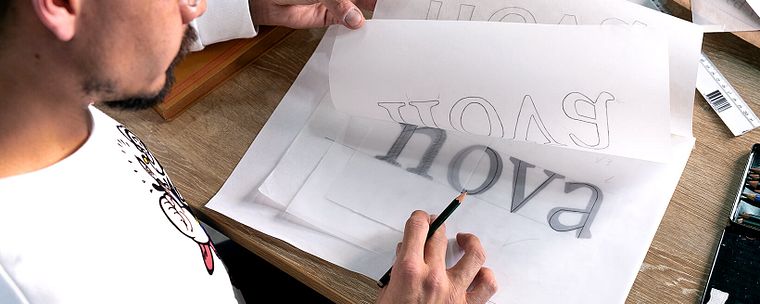
Aprenderás a analizar, reinterpretar y digitalizar tipografías históricas, aplicando técnicas de caligrafía, dibujo y software especializado para crear fuentes contemporáneas basadas en modelos clásicos.
El curso está orientado a personas con conocimientos intermedios de diseño gráfico o tipografía, pero no es necesario ser experto. Se recomienda familiaridad básica con diseño y herramientas digitales.
Necesitarás acceso a software de diseño vectorial como Illustrator y un editor de fuentes como Glyphs, además de papel, lápiz, pluma chata y escáner o cámara para digitalizar bocetos.
La caligrafía con pluma chata ayuda a comprender la estructura y proporciones de las letras, facilitando la creación de bocetos que luego se digitalizan y perfeccionan en software tipográfico.
Un revival implica reinterpretar y adaptar una tipografía histórica a necesidades actuales, mientras que copiar solo replica formas sin ajustes funcionales o estéticos para el contexto contemporáneo.
Aprenderás a estructurar tanto fuentes individuales como familias tipográficas, incluyendo variantes y sistemas coherentes a partir de modelos históricos y criterios funcionales actuales.
La investigación histórica es clave para analizar especímenes antiguos, identificar características morfológicas y fundamentar decisiones de diseño en proyectos de revival tipográfico.